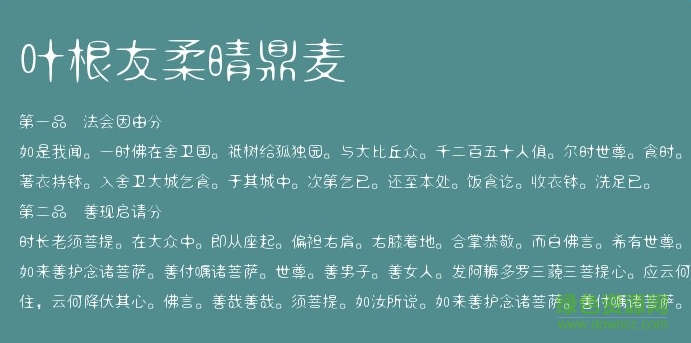
葉根友柔晴鼎麥字體是一款文雅細膩風格字體軟件,柔晴鼎麥體筆畫圓滑卻不失工整,字里行間透露著濃濃的柔情,整體效果十分好看,深受廣大年輕人喜愛,還有更多好看字體歡迎來綠色資源網(wǎng)下載體驗!
葉根友柔晴鼎麥字體是一款優(yōu)雅而柔情蜜意的字體,整個字看了后,整個人是不是都感覺身體被掏空了?到底有沒有這個掏空功能,誰試誰知道~